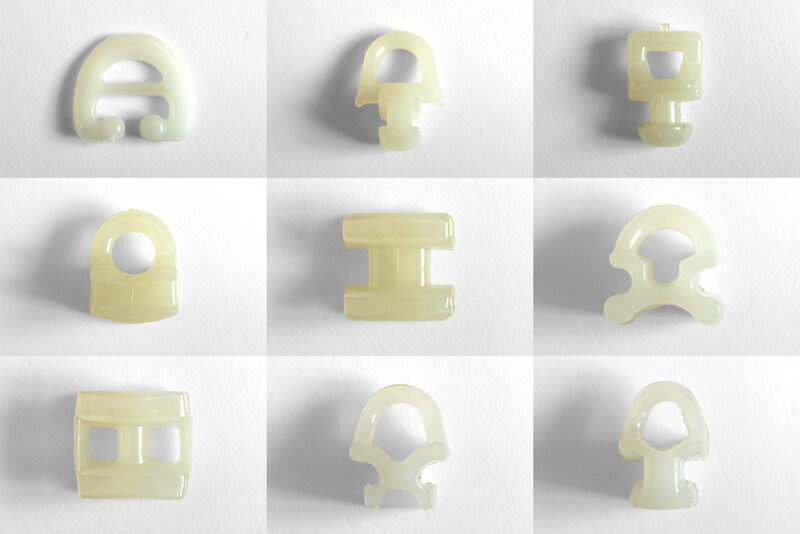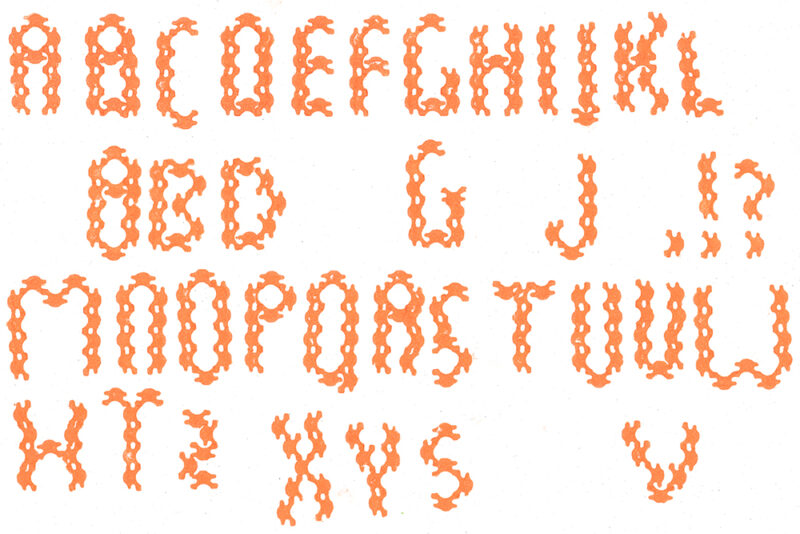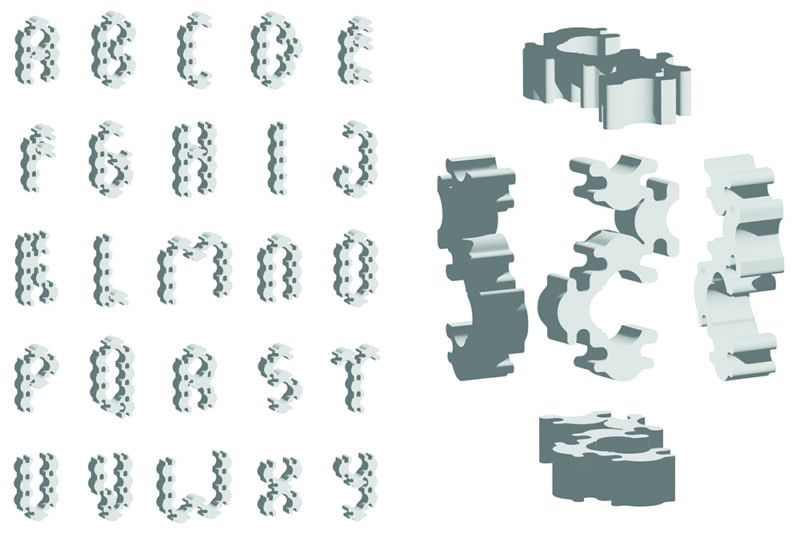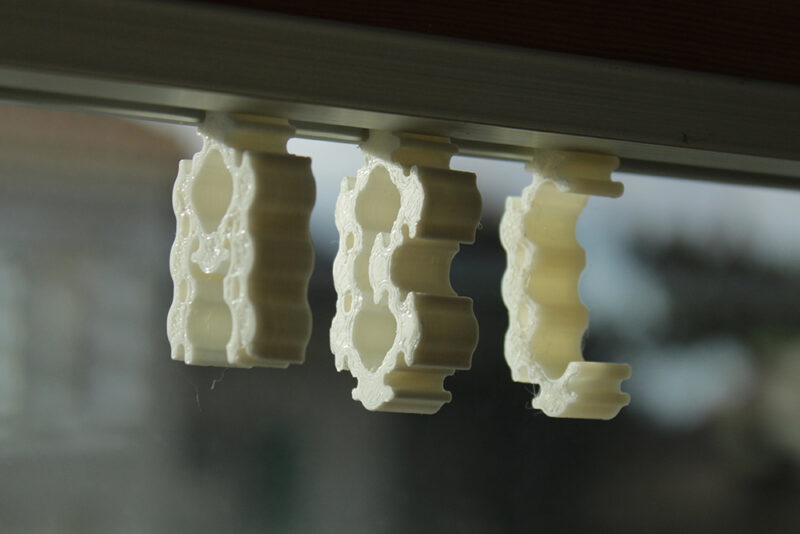
Silent Gliss
Die Projektarbeit gründet auf einen Sammlungsbestand marktüblicher Vorhanggleiter. Aus deren Analyse gehen digitale Modularformen als Schriftbausteine hervor. Zu Buchstaben verbunden sind diese nach dem 3D-Druck räumlich erfahrbar. Zurückgeführt in die Funktion als Vorhanggleiter sind die Buchstaben in der Vorhangschiene verschiebbar. Die Arbeit ist als Prototyp zu deuten. Mit seiner Weiterentwicklung geht die Konkretisierung zusätzlicher Anwendungsmöglichkeiten einher.